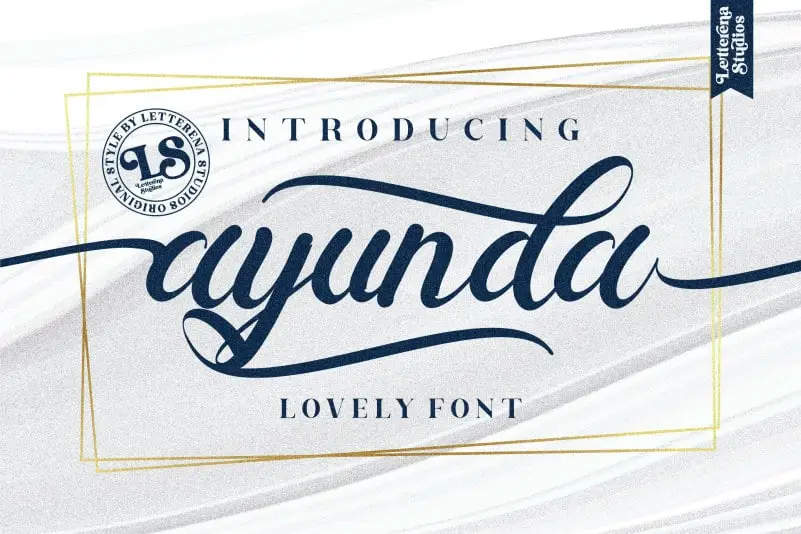
Ayunda Calligraphy Font é uma fonte aquarela feita especialmente para aqueles que adoram fazer arte com palavras. Com seu estilo potente e encantador, essa fonte é ideal tanto para quem deseja criar cartões de casamento ou material de escrita de qualidade quanto para quem busca algo um pouco mais divertido para enfeitar suas postagens no Instagram ou outros canais de mídia social. A Ayunda Calligraphy Font permite que você transforme qualquer projeto digital em uma obra-prima, seja para agradar aos olhos ou para tornar as experiências pessoais únicas e memoráveis. A vantagem deste tipo de fonte é que ela é PUA (Postscript Universal Access) encodada, o que significa que você pode facilmente acessar todos os caracteres e desenhos especiais sem dor de cabeça. A Ayunda Calligraphy Font não apenas oferece diversão em cada palavra escrita, mas também a oportunidade de transformar simples textos em verdadeiras obras de arte. Com ela, qualquer projeto se torna uma viagem visual que encanta quem vê e permite que você construa memórias emocionantes com amigos e familiares através dos seus canais online ou offline.